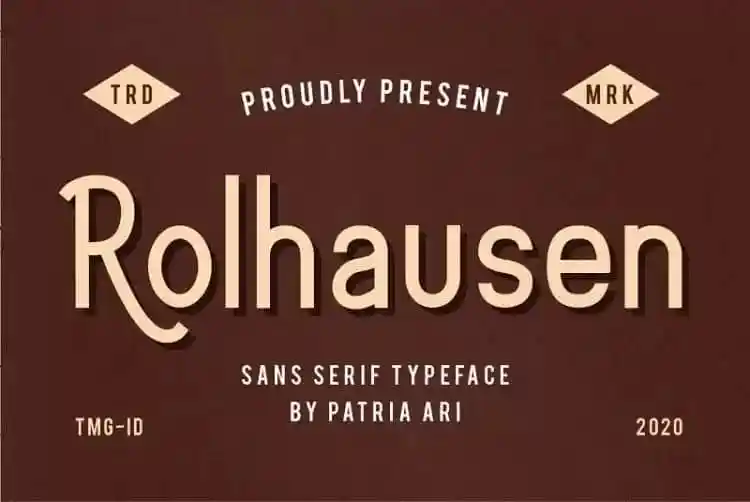
A Rolhausen Sans Serif é uma elegante tipografia sans-serif que oferece um toque moderno e geométrico. Seu design clean e simples se destaca pelo seu estilo grotesco e humanista, criando uma fachada de simplicidade que é igualmente adequada para uso em logotipos, rótulos de produtos, embalagens, cartões de convite ou qualquer outro tipo de mídia visual. Ela é perfeitamente adaptável a um vasto range de aplicações visuais e está projetada para atender a uma ampla gama de necessidades gráficas. Esta fonte é particularmente indicada quando você precisa uma tipografia fresca e moderna, que se destaca em qualquer ambiente visual. É uma escolha ótima tanto para o uso em títulos quanto no desenvolvimento de logotipos ou rótulos, sem comprometer a legibilidade. Seja qual for sua necessidade gráfica, a Rolhausen Sans Serif é um atalho ideal.